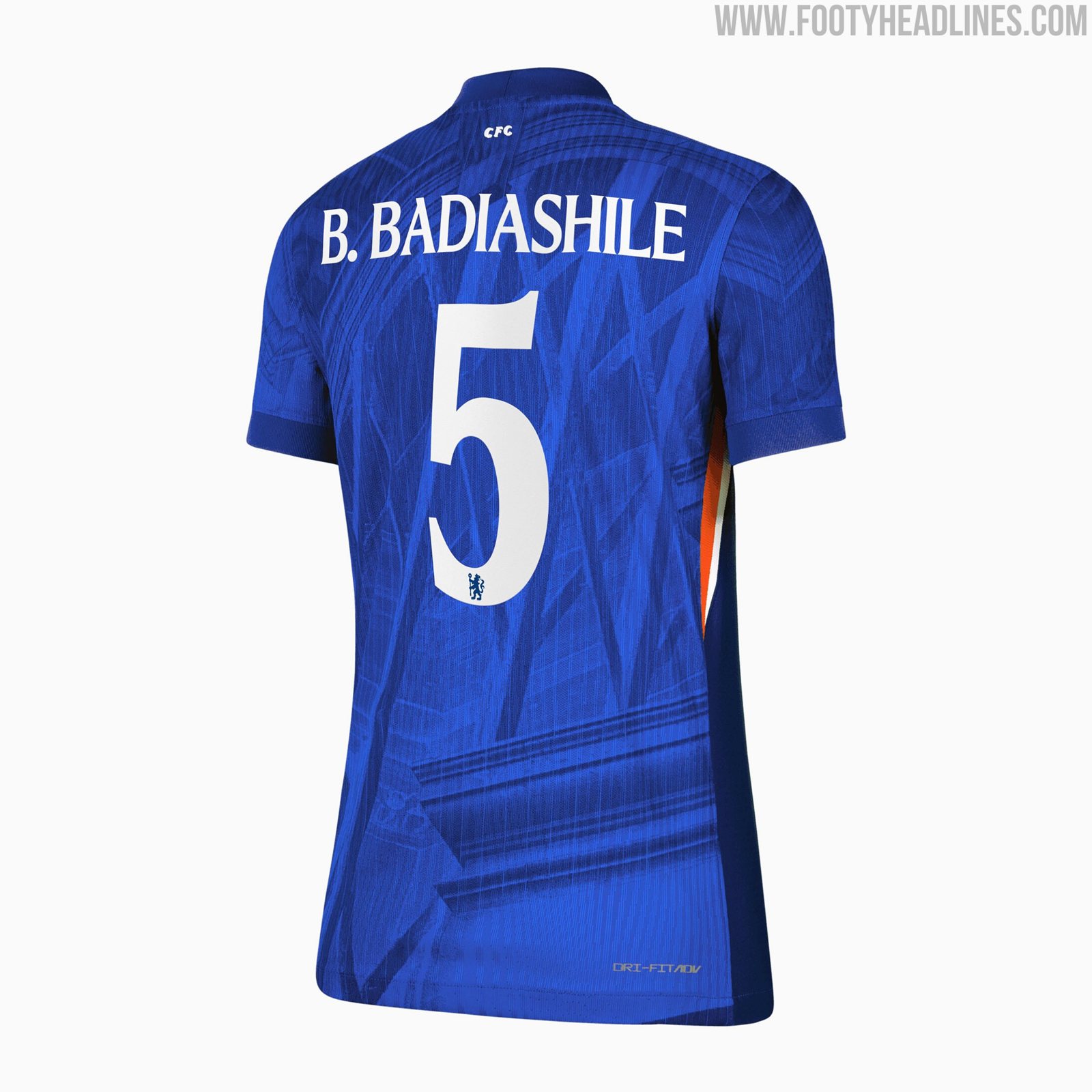
Rilasciato il nuovo font per la maglia del Chelsea 25-26
- Nuovo Font Maglia: Il Chelsea FC ha svelato un nuovo font per le maglie che verrà utilizzato a partire dalla stagione 2025-26, sostituendo il design del 2019.
- Estetica del Font: Il nuovo font introduce un'estetica più moderna e audace, pur mantenendo un'impronta tradizionale, con numeri e lettere condensati e curve eleganti.
Il Chelsea FC ha presentato un nuovissimo font per la maglia che sarà utilizzato a partire dalla stagione 2025-26. Si tratta del primo aggiornamento del carattere del club in sei anni, che sostituisce il design che ha debuttato nel 2019 e che è stato utilizzato fino alla campagna 2024-25.
Il nuovo carattere della maglia del Chelsea 25-26
Il nuovo font della maglia del Chelsea 25-26 introduce un'estetica modernizzata e più audace, pur mantenendo un'impronta tradizionale adatta all'identità del club.
I numeri e le lettere sono leggermente più condensati rispetto allo stile precedente, con curve eleganti e serif raffinati che conferiscono al font un aspetto più contemporaneo ma distinto.